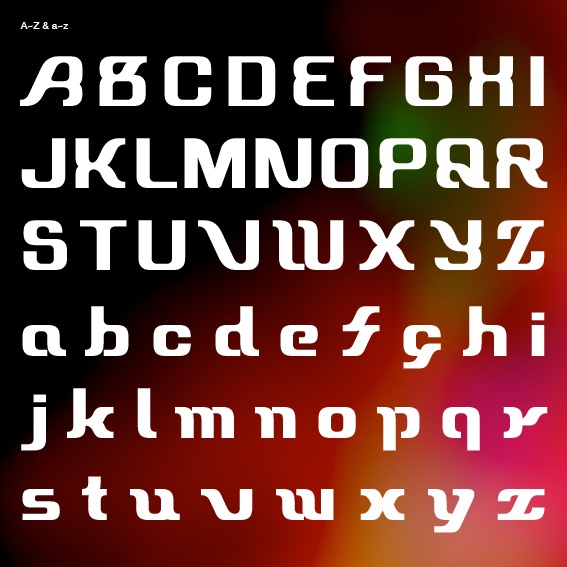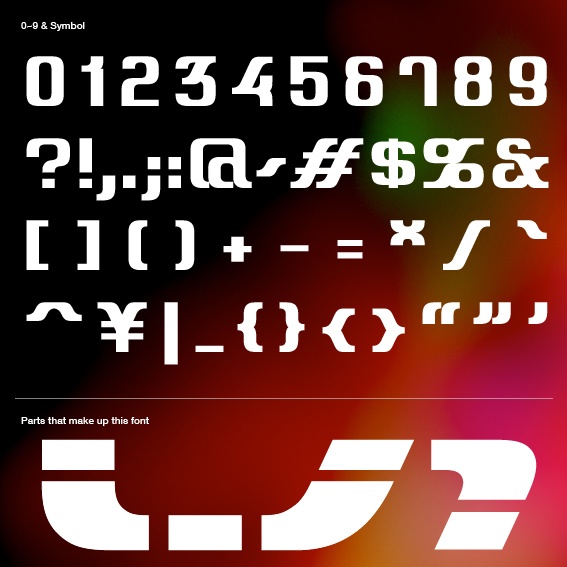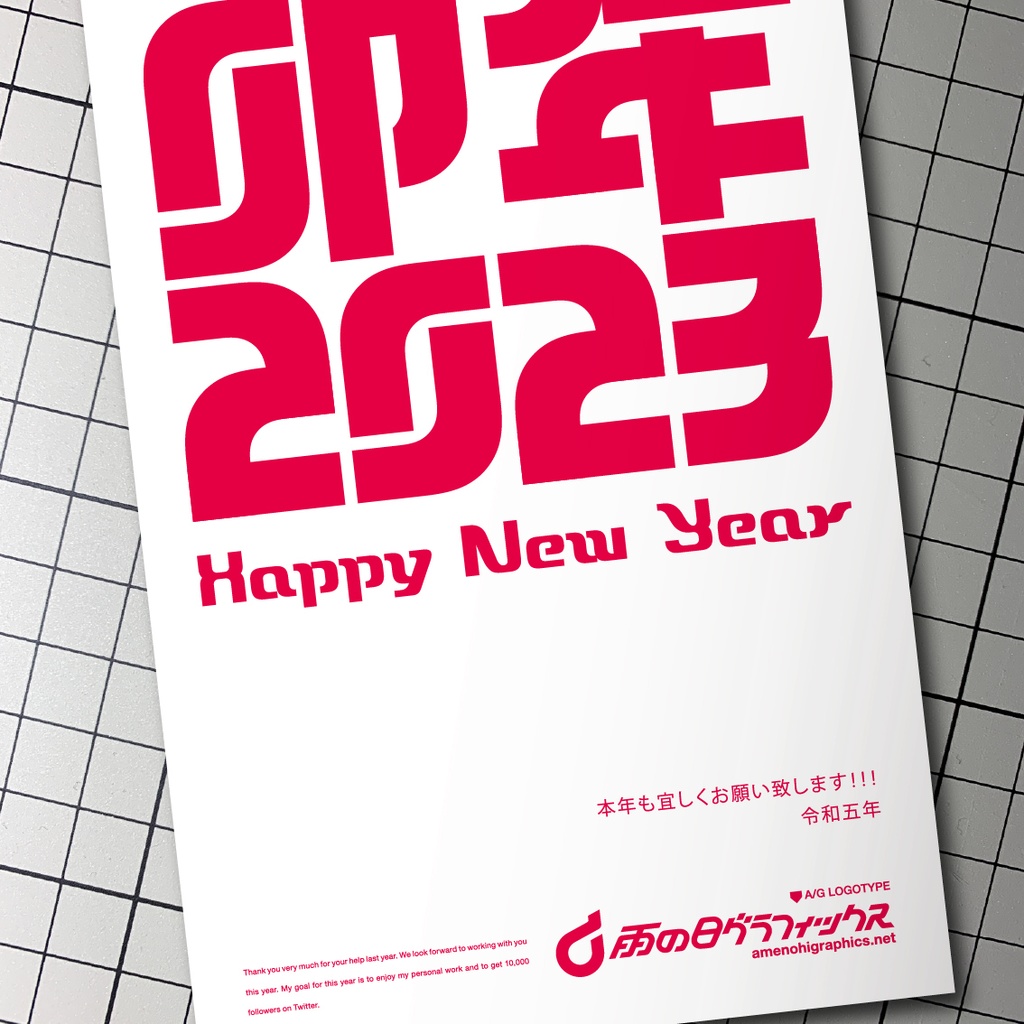
【無料】フリーフォント「Fury」
【このフォントについて】 丸みを帯びたテクノ風フォントを目指し作ったオリジナルフォントです。 数種類のパーツから文字を組み上げ、可読性を保ちながら個性的な形を探求しました。 ネーミングはあることで激怒(英語:Fury)したことをきっかけに作字した文字をベースに制作したので採用しました。今はもう怒ってません。 また、「無料ダウンロード」と「投げ銭」で内容の違いはありません。 もしも応援していただけるのならば…新たなフォント制作やその他グッズのモチベーションとなりますので何卒宜しくお願い致します!! 【収録文字】 ・アルファベットA-Z、a~z、数字0~9、記号各種 全94文字 【同梱ファイル】 ・フォントデータ(.otfファイル) ・readme 【 利用について】 ・ 個人利用可能です。 ・雨の日グラフィックスのSNSアカウントをフォローしている方に限り商用利用も可能です。 Twitter: https://twitter.com/amenohigraphics Instagram: https://www.instagram.com/amenohigraphics/ ・ 加工・変形してご利用可能です。 ・ 利用報告は必要ありませんが言っていただければ製作者が喜びます。 【 当フォントの禁止事項】 ・ ロゴマーク等、商標登録、意匠登録すること。 ・フォントデータの譲渡、再配布、販売。 ・ データを改変して販売、再配布。 ・ 当フォントをメインとした商品の販売。 ・ 誹謗中傷・公序良俗に反する目的での使用。 ・ワシが作ったなどの自作を主張する行為。 【注意事項】 ・ご使用の際はreadmeを一度ご一読ください。 ・動作確認はAdobe Illustrator 2023のみで行いました。 ・ 著作権は放棄しておりません。 ・当フォントを利用したことにより生じた損害について作成者は一切の責任を負いません。 ・使用方法や動作の不具合等についてのご質問には対応できません。 ・予告なくバージョンアップやフォントの配布を終了する場合があります。 【お問い合わせ】 雨の日グラフィックス website : https://amenohigraphics.net Twitter: https://twitter.com/amenohigraphics Instagram: https://www.instagram.com/amenohigraphics/ メール : amenohigraphics@gmail.com